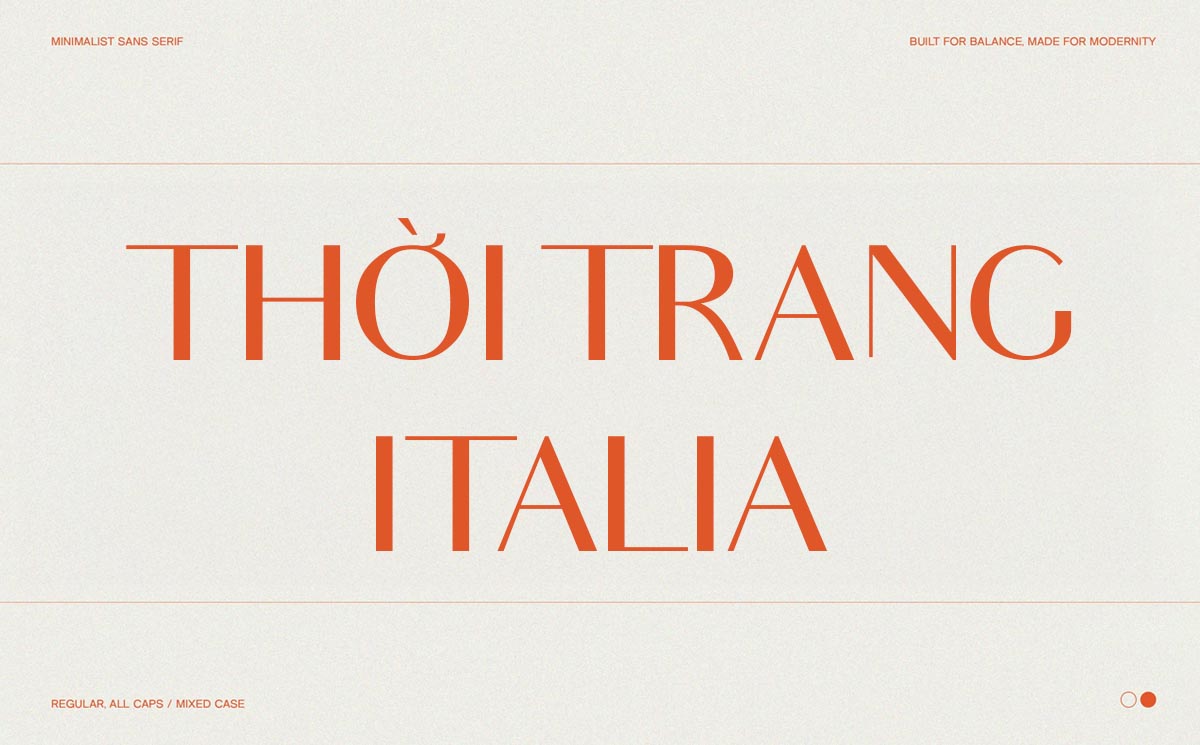
Font chữ Sans Serif hiện đại không chân SVN Audrey – Thanh lịch, tối giản và chuyên nghiệp
Font SVN Audrey là gì?
SVN Audrey là một font chữ Sans Serif hiện đại, nổi bật với thiết kế không chân (Sans Serif), đường nét thanh mảnh và cân đối. Font mang phong cách tối giản nhưng vẫn toát lên vẻ sang trọng, phù hợp với nhiều nhu cầu thiết kế như poster, banner, logo, nhận diện thương hiệu, website, mạng xã hội hay các ấn phẩm quảng cáo.
Với khả năng hiển thị rõ ràng ở nhiều kích thước, SVN Audrey là lựa chọn lý tưởng cho những ai yêu thích phong cách thiết kế hiện đại, tinh tế và chuyên nghiệp.
Điểm nổi bật của font SVN Audrey
- Thiết kế Sans Serif hiện đại, không chân.
- Đường nét thanh lịch, tối giản và dễ đọc.
- Phù hợp với cả tiêu đề và nội dung ngắn.
- Hỗ trợ tiếng Việt đầy đủ sau khi Việt hóa.
- Dễ dàng kết hợp với các font Serif hoặc Script trong thiết kế.
Ứng dụng của SVN Audrey
Font SVN Audrey được sử dụng rộng rãi trong nhiều lĩnh vực như:
- Thiết kế logo và bộ nhận diện thương hiệu.
- Thiết kế banner, poster, brochure.
- Tiêu đề website, landing page.
- Bài đăng Facebook, Instagram, TikTok.
- Thiết kế bao bì sản phẩm.
- Slide thuyết trình và tài liệu doanh nghiệp.
Nhờ phong cách hiện đại và tinh gọn, SVN Audrey giúp sản phẩm thiết kế trở nên cao cấp và thu hút hơn.
Vì sao nên chọn SVN Audrey?
Nếu bạn đang tìm kiếm một font chữ vừa hiện đại, vừa dễ sử dụng thì SVN Audrey là lựa chọn rất đáng cân nhắc. Font có độ cân đối tốt, khả năng hiển thị sắc nét trên cả màn hình và bản in, đồng thời dễ phối hợp với nhiều phong cách thiết kế khác nhau.
Đặc biệt, phiên bản Việt hóa giúp người dùng dễ dàng sử dụng trong các dự án tiếng Việt mà vẫn giữ được vẻ đẹp nguyên bản của bộ font.
Thông tin font
- Tên font: SVN Audrey
- Phong cách: Sans Serif
- Phân loại: Font chữ không chân hiện đại
- Hỗ trợ: Tiếng Việt đầy đủ
- Ứng dụng: Thiết kế đồ họa, branding, UI/UX, in ấn, mạng xã hội
Kết luận
SVN Audrey là font chữ Sans Serif hiện đại mang phong cách tối giản, thanh lịch và chuyên nghiệp. Với khả năng hiển thị đẹp, hỗ trợ tiếng Việt đầy đủ và tính ứng dụng cao, đây là một trong những font chữ phù hợp cho designer, marketer cũng như người làm nội dung. Nếu bạn muốn tạo nên những thiết kế tinh tế và hiện đại, SVN Audrey chắc chắn là một lựa chọn đáng để bổ sung vào bộ sưu tập font của mình.